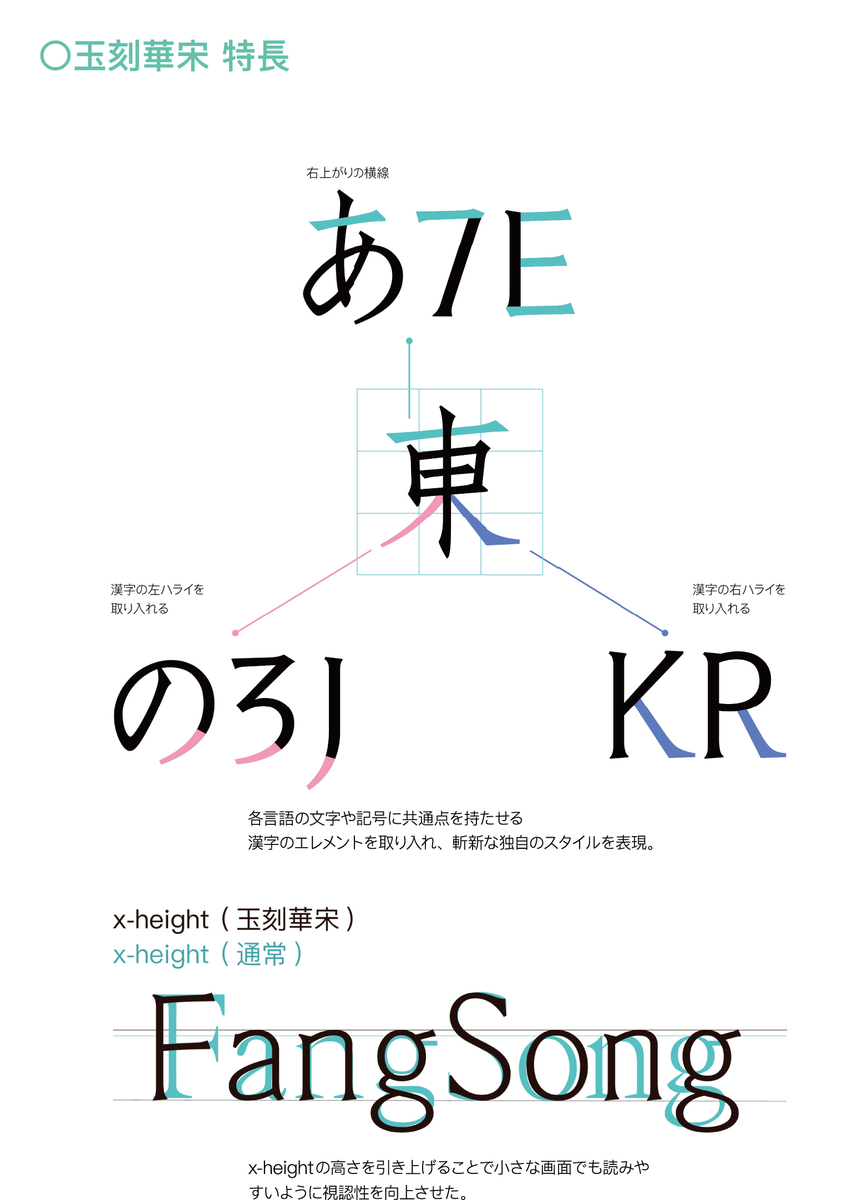
ダイナフォント全書体が使える年間ライセンス「DynaSmart V」に2021年新宋朝体「玉刻華宋」など合計19書体が5月13日から追加収録
ダイナコムウェアは、ダイナフォント年間ライセンス「DynaSmart V」「DynaSmart 教育機関向けプラン」「DynaSmart 学生版」ユーザーに向けて、古典的な趣の宋朝体に新たな風を吹き込んだエレガントな2021年新書体「玉刻華宋(ぎょっこくかそう)」を含むダイナフォント19書体を2021年5月13日(木)より提供を開始した。
「DynaSmart V」には、今回、2021年新書体「玉刻華宋」以外にも人気書体「麗雅宋W5/W7/W9」「祥南行書体W5」のOpenTypeフォントStdN版や、元号「令和」発表時の“令”の字形に対応した、厳格な楷書体を現代でも使いやすいように視認性と判別性を高めたデザインの「楷書体シリーズ 令和版」6ウェイトのTrueTypeフォント版を追加収録された。
デジタルでの使用に適した最新の宋朝体「玉刻華宋」
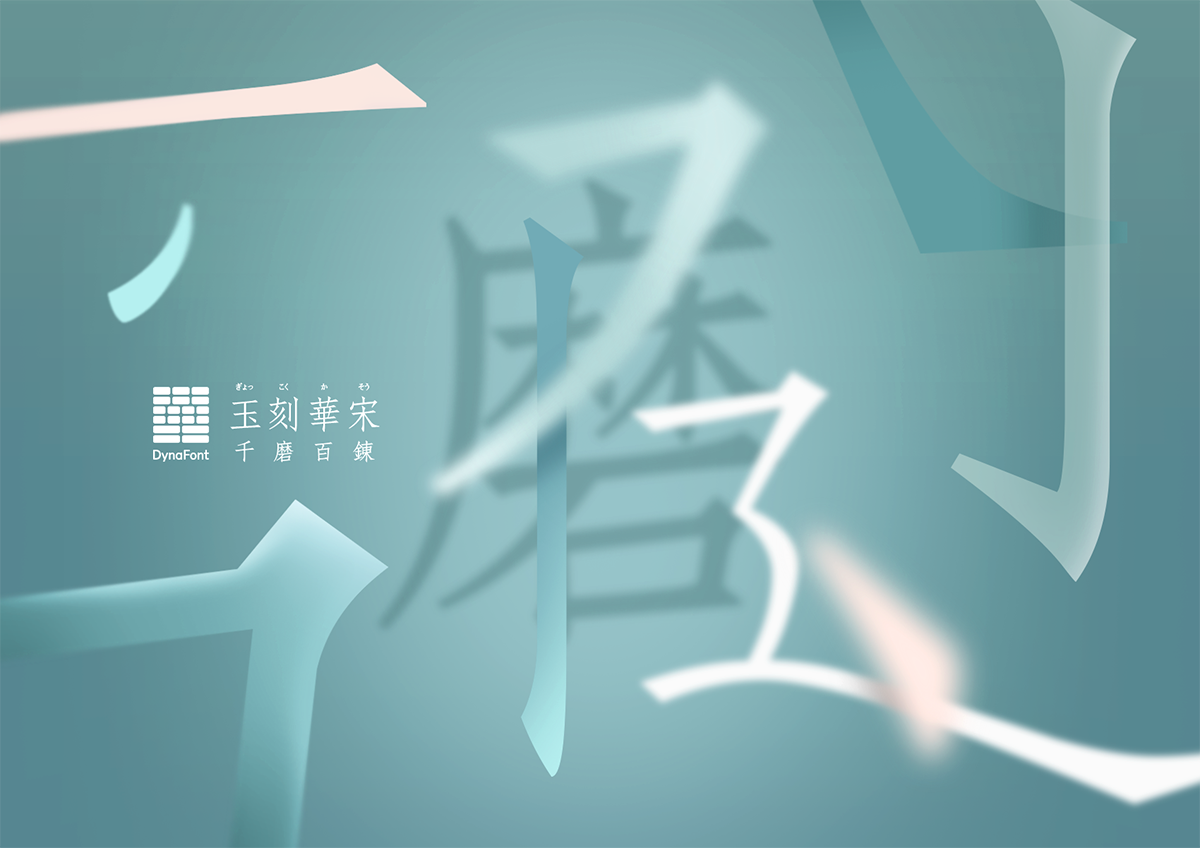
「玉刻華宋」は、中華民国初期の宋朝体から実際に印刷された書体見本を参考に、明朝体と楷書体のエレメントを兼ね備えた縦長の字形と力強く鋭い画線を特長にした書体。
古代ローマの碑文石や人文主義的(Humanist)な手書き書体も取り入れており、漢字のエレメントに個性的な欧文や記号と融合させることで、視覚的にもバランスが整うように設計。
ディスプレイ表示での読みやすさに様々なデバイスでの高い適応力を追求し、“千磨百錬”の如く磨きあげることで、デジタル時代において、古典的な文字の趣に一味違ったエレガントな雰囲気をもたらす書体になっているとのこと。
「玉刻華宋」書体見本
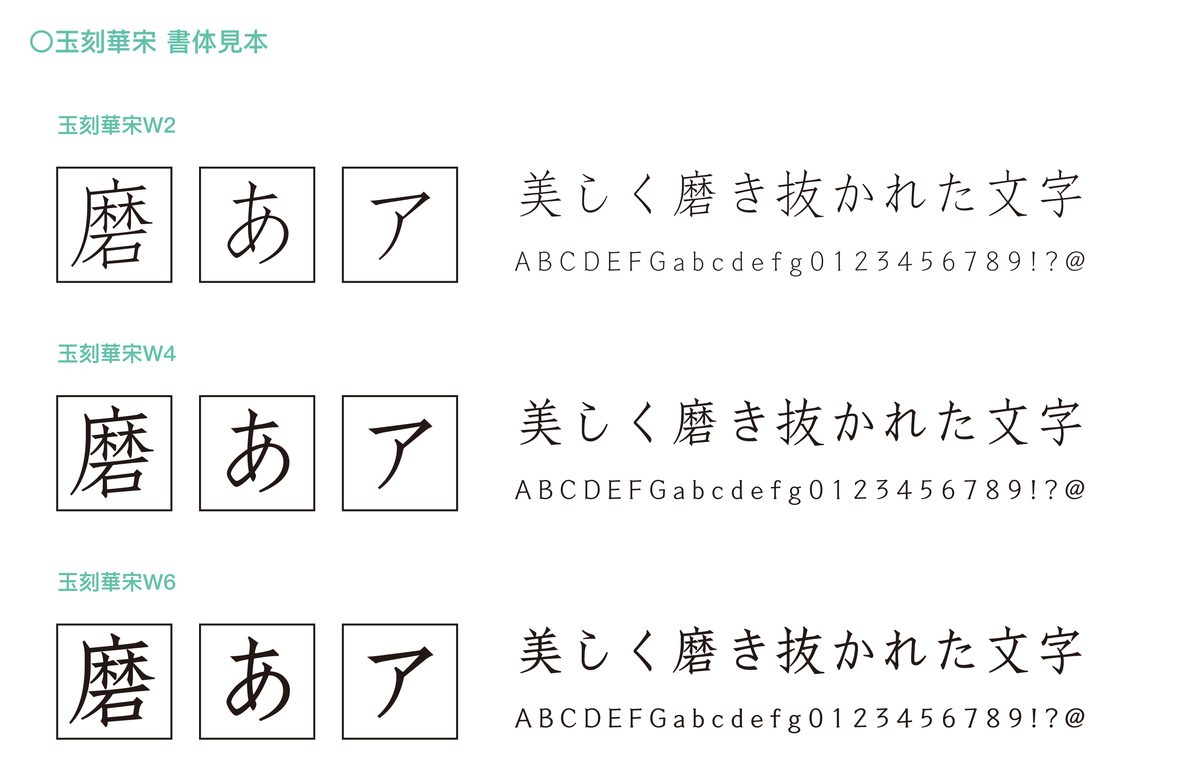
「玉刻華宋」特長
「玉刻華宋」活用例
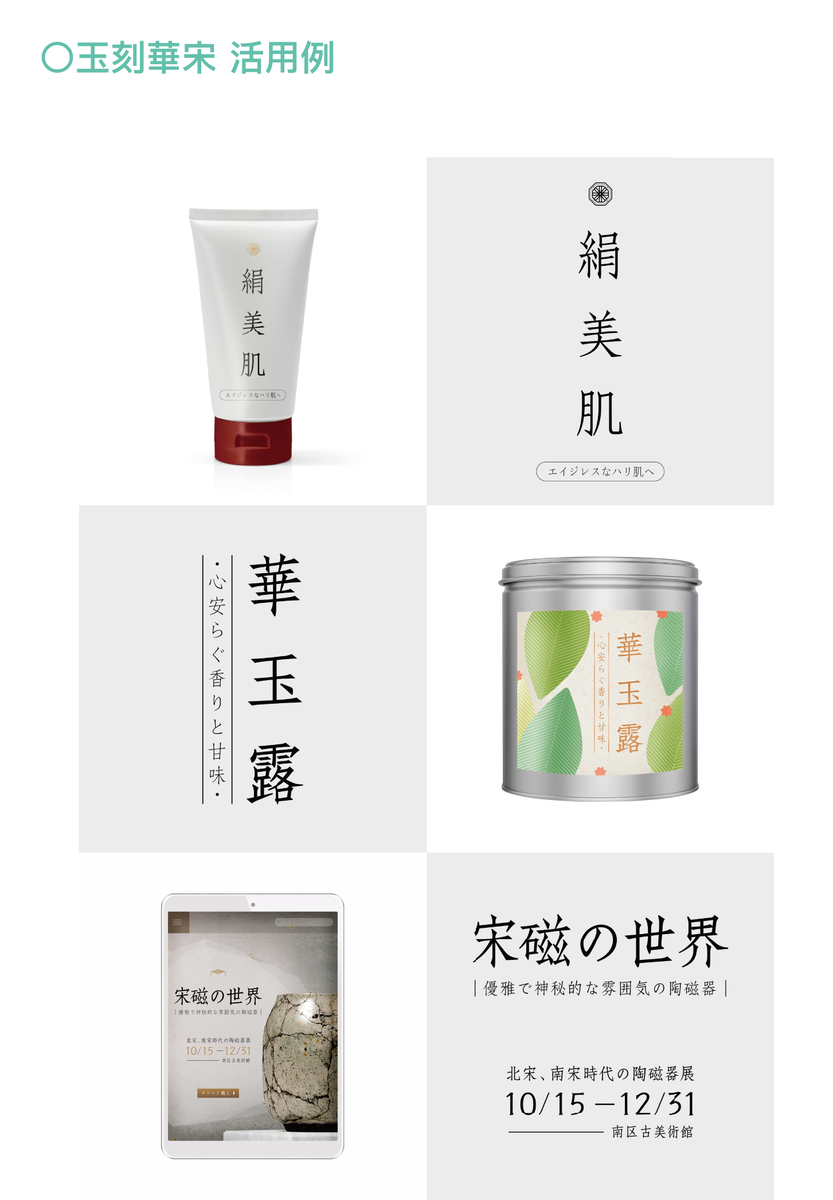
ダイナフォントの2種類の宋朝体「新宋体」と「玉刻華宋」を比較してみた
ダイナフォントでは宋朝体として、玉刻華宋の前にメディアミックスなどされて人気を博した「物語シリーズ」などで使用されてきた新宋体を発表している。
そこで新宋体と玉刻華宋を並べて比較してみた。
並べてみると、漢字とかなは新宋体のほうがより縦長でスマート、また、ストロークから鋭い印象を受ける。
逆に玉刻華宋はデジタル用にカスタマイズされているためだろうか、新宋体より柔らかく滑らかな印象を受けた。
DF玉刻華宋W2
DF玉刻華宋W4
DF玉刻華宋W6